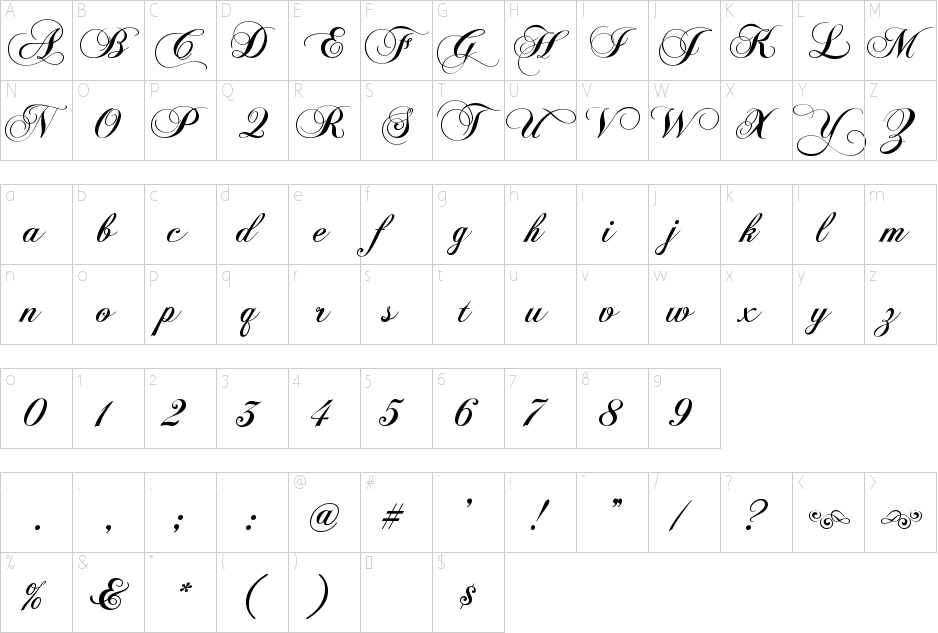
Рекомендации по созданию медицинского логотипа | Дизайн, лого и бизнес
Эмблема для медицинского учреждения также важна, как и для любой компании. Он будет сообщать потенциальным клиентам о названии и сфере деятельности организации.
Выбор иконки
Для эмблемы иконка является основным элементом, отражающим специфику работы учреждения.
Ее следует подбирать согласно медицинской тематике. Поэтому наиболее оптимально использовать такие элементы, как:
- Картинки зубов (в случае стоматологии), глаз (для офтальмологической клиники) и т. п. То есть, то изображение, которые даст понять посетителям, какой вид медицинских услуг предоставляется в данном учреждении.
- Абстрактная символика. Очень распространены греческие символы медицины на подобии «красного креста», сосуда Гигеи или посоха Асклепия.
- Изображение человеческой фигуры. Тут также важно учитывать специализацию клиники. Например, если это детское учреждение, то желательно изобразить на эмблеме детей.
Выбор цвета
Цветовая палитра будущего логотипа крайне важна, особенно если речь идет о медицинском учреждении. Желательно выбирать цветовую окраску, которая ассоциируется людьми именно с этой сферой. Оптимальные цвета для медицинского логотипа:
- красный
- синий
- зеленый
Выбор шрифта
Выбранный шрифт должен подходить иконке, а также общей задумке. Помимо этого, следует учитывать, что логотип разрабатывается для медицинского учреждения. Поэтому шрифт должен быть:
- Читабельным.
Это крайне важно для логотипа клиники. Больные и посетители должны иметь возможность легко прочитать название учреждения. - Гармоничным. Важно подбирать шрифт, который будет сочетаться как с иконкой, так и с окраской лого. Например, если иконка массивная, то и шрифтовой стиль следует использовать соответствующий.
- Сдержанный. Нежелательно использовать шрифты, которые перегружены узорами или другими деталями. Это ухудшит читаемость и сделает общий вид логотипа неуместным.
Для логотипа медицинского учреждения рекомендуется использовать шрифты:
- Oranienbaum
- Comfortaa
- Prosto
- Roboto
- Revalia
- Fondamento
- Esqadero
- Caviar Dreams
Дополнительные советы
Далее представлены рекомендации, учет которых также важен при разработке логотипа для медицинской организации.
- Делайте эмблему сдержанной. Не нужно использовать сложные изображения или слишком много текста. Логотип должен быть легко читаемый и передавать только важную информацию.
- Используйте один-два вида шрифта. Желательно остановиться на одном шрифтовом стиле, но если необходимо использование двух, то нужно учитывать их сочетаемость между собой.
- Не применяйте много цветов. Медицинский логотип должен быть сдержанным. Но если нужно использовать несколько цветов, то выбирайте сочетающиеся цвета (не более 4-х).
- Не заполняйте логотип полностью. Нужно оставить пустые места около эмблемы и другими деталями. Это значительно облегчает читаемость каждого элемента в уменьшенном масштабе.
- Используйте векторный формат. Он облегчит дальнейшее применение логотипа при его размещении на вывески или сайты.
Этот шрифт позволяет вам выразить полушрифт с засечками и отмечен изгибом, чтобы улучшить общий вид вашего контента.
Extravaganzza
Extravaganza — это уникальный и привлекательный тип шрифта, который доступен как в формате Regular, так и Bold.
Шрифт Chunk Slat Serif
Шрифт Chunk основан на шрифте с планками с засечками. Дизайн унаследован от напоминающих старые американские плакаты, ксилографии и газетных заголовков. Поскольку он в основном используется для отображения, Chunk может оказаться лучшим доступным шрифтом для заголовков и заголовков.